今回は、ネオンがきらめく近未来の都市や、退廃的なデジタル世界を演出できる「サイバーパンク」の雰囲気にぴったりな日本語フォントをご紹介します。
サイバーパンクといえば、高層ビルが立ち並ぶ夜の街、ノイズ混じりのモニター、サイバー空間、ハッカー、機械化された身体、そしてどこか危ういアンダーグラウンド感。文字にも、無機質な硬さやデジタル感、少し壊れたような違和感があると、世界観が一気に引き締まります。
今回は、グリッチ感のあるフォント、角ばったデジタル系フォント、ネオンやSF作品に合うクールな日本語フォントをピックアップしました。ゲームUIや映像タイトル、MV、ポスター、近未来系のロゴ制作などにぜひ活用してみてください。
瀞ノグリッチ黒体
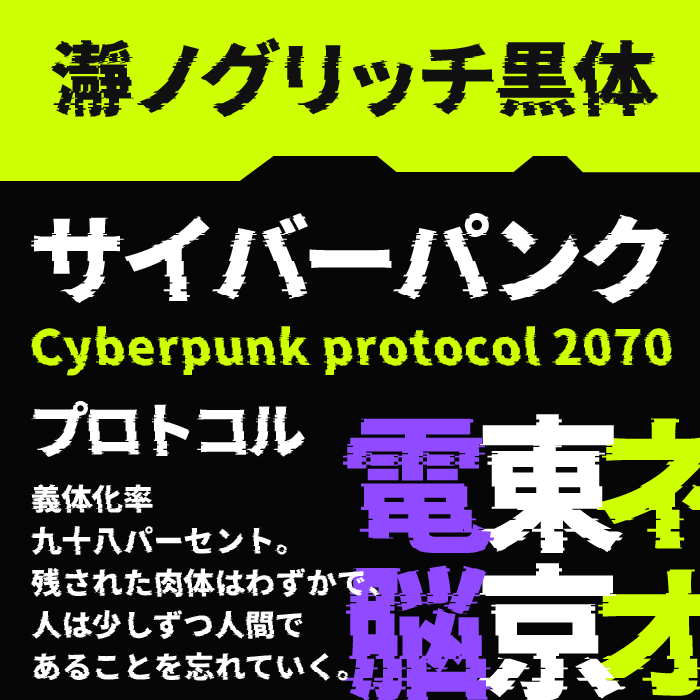
| 活用シーン例 | グリッチ演出、システムエラー表現、退廃的SFデザイン、電脳世界、未来都市ビジュアル |
瀞ノグリッチ黒体は、文字の輪郭がノイズで崩れたようなグリッチ加工が特徴的なフォントです。
通信障害やシステムエラーを連想させるビジュアルが強く、サイバーパンク作品でよく見られる“壊れた未来”や“不安定なデジタル社会”を表現するのにぴったりです。かなりインパクトの強い演出ができます。
ゴチカクット
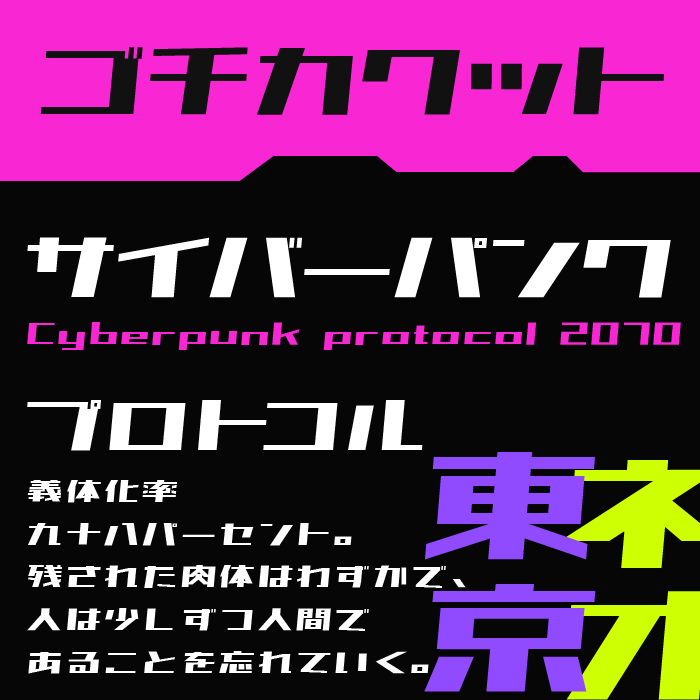
| 活用シーン例 | サイバーパンク作品、近未来UI、SFポスター、ゲームロゴ、電脳都市デザイン |
ゴチカクットは、鋭角的でスピード感のある字形が特徴的なフォントです。
直線を多用したシャープなデザインが近未来的なUIやSF作品を連想させ、無機質でクールな世界観を演出できます。サイバーパンクらしいネオンカラーやハイテク感のあるビジュアルと非常に相性が良く、都市型SFデザインにぴったりなフォントです。
瀞ノクーゲル明朝
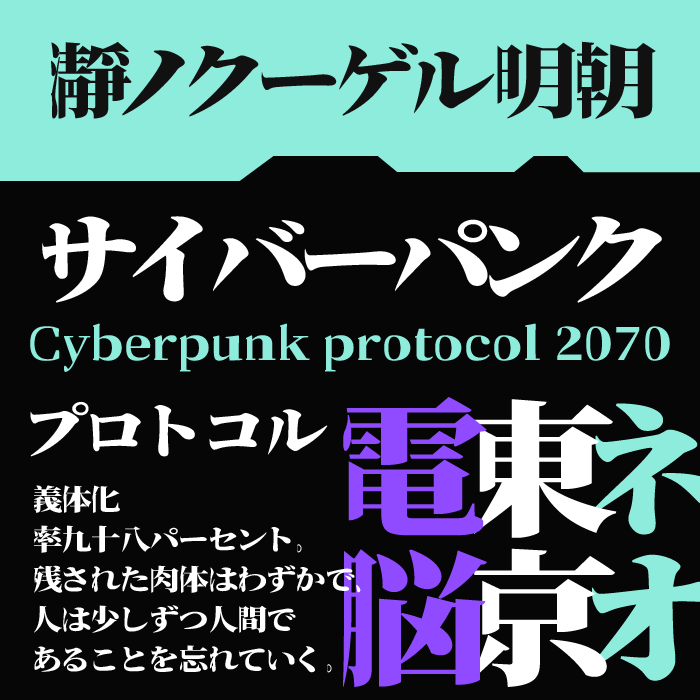
| 活用シーン例 | 広告デザイン/サムネイル/テロップ/バナー/パッケージ/ポスター/同人誌 |
瀞ノクーゲル明朝は、伝統的な明朝体に鋭いエッジや独特な抑揚を加えたフォントです。
クラシカルな雰囲気を持ちながらも、どこか異質で未来感のある造形が特徴で、和とテクノロジーが融合したサイバーパンク作品とも相性抜群です。近未来と退廃感が共存する独特な空気感を演出できます。
JikiTourai
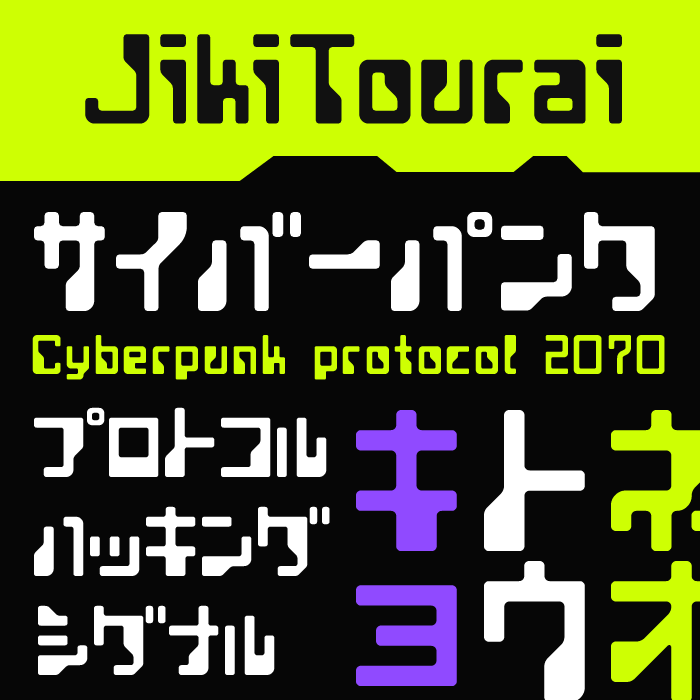
| 活用シーン例 | レトロフューチャー、ゲームUI、ドットデザイン、電子機器風グラフィック |
JikiTouraiは、大胆で太めのドット構造が特徴的なフォントです。
レトロゲームや古い電子機器を思わせるピクセル感がありながら、どこか未来的なインターフェースにも見える絶妙なデザインが魅力です。80年代〜90年代SF作品のようなレトロフューチャー感を表現したい場面におすすめです。
エイプリルゴシック
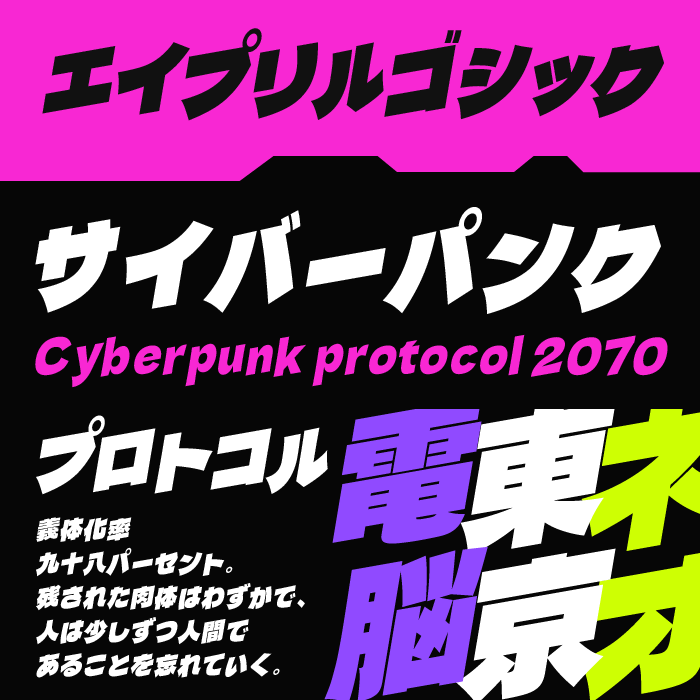
| 活用シーン例 | SFアニメタイトル、近未来レースゲーム、アクション系デザイン |
エイプリルゴシックは、太く傾斜のついたダイナミックな字形が特徴的なフォントです。
勢いのあるフォルムがスピード感やアクション性を感じさせ、アニメ調のサイバーパンク作品や近未来レースゲームのような派手な世界観とよく合います。視線を一気に引き込む強い存在感が魅力です。
Deep South
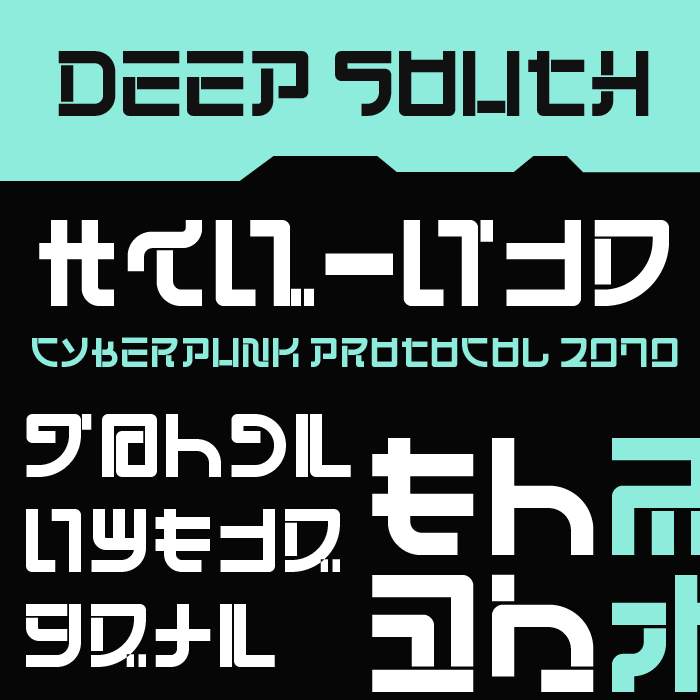
| 活用シーン例 | AIデザイン、未来デバイスUI、テクノロジー系ビジュアル、電子基板風デザイン |
Deep Southは、幾何学的なパーツを組み合わせたような独特な字形が特徴のフリーフォントです。
人工知能や電子基板、未来のデバイス画面を連想させるデザインになっており、かなり無機質でハイテクな印象があります。王道サイバーパンクというより、よりテクノロジー寄りな未来感を表現したい場面におすすめです。
地方野球場電光掲示板
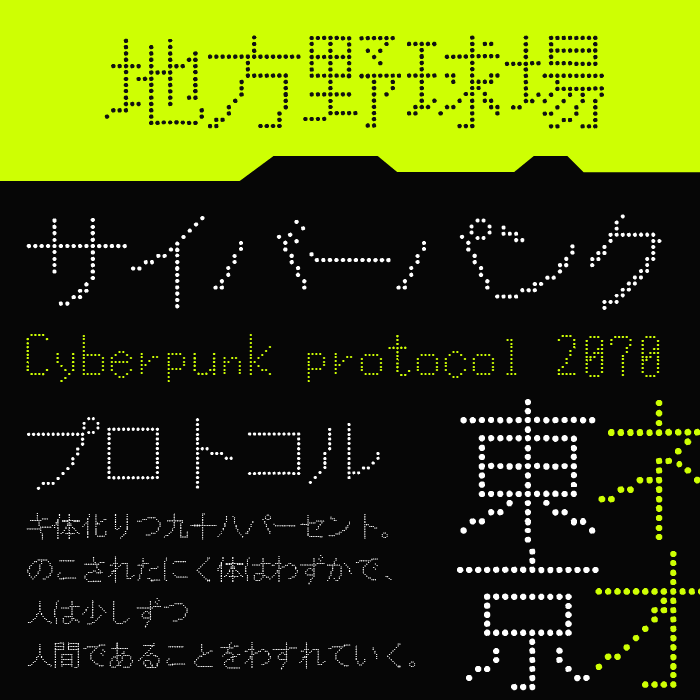
| 活用シーン例 | LED表示風デザイン、ホログラムUI、電光掲示板風演出、未来都市表現 |
地方野球場電光掲示板フォントは、小さなドットを並べて構成された独特な字形が特徴的な、日本語フリーフォントです。一見アナログな電光掲示板を思わせながらも、点で構成された文字表現が未来都市のLED表示やホログラム表示にも見え、独自のサイバーパンク感を演出できます。少し変化球な近未来表現をしたいときにおすすめです。
アルファパーツ
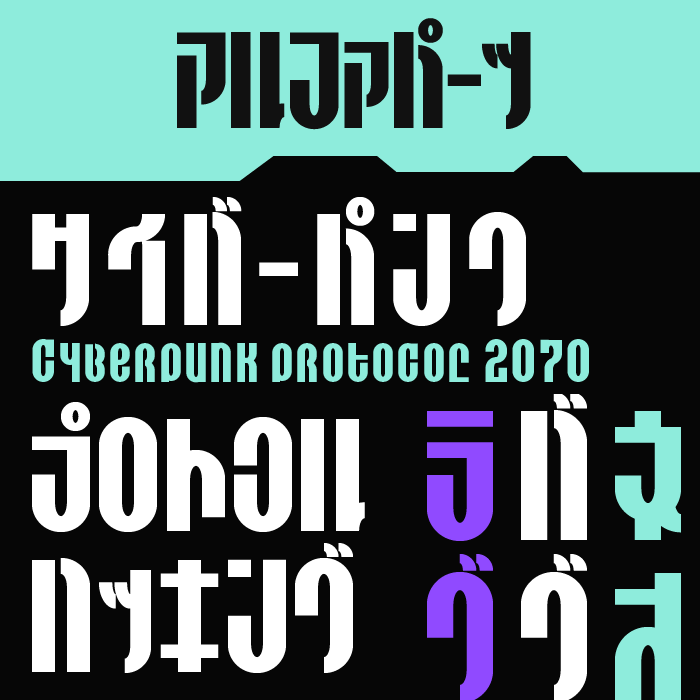
| 活用シーン例 | 海外SF作品風デザイン、映画タイトルロゴ、近未来、サイバー演出 |
アルファパーツは、極端に縦長なシルエットと独特な文字の切れ込みが特徴的なデザインフォントです。海外SF映画のタイトルロゴを思わせる強烈な個性があり、一目で近未来感を演出できます。日本語フォントと組み合わせることで、一気に本格的なサイバーパンク世界観を作り込めます。
でんきチップ
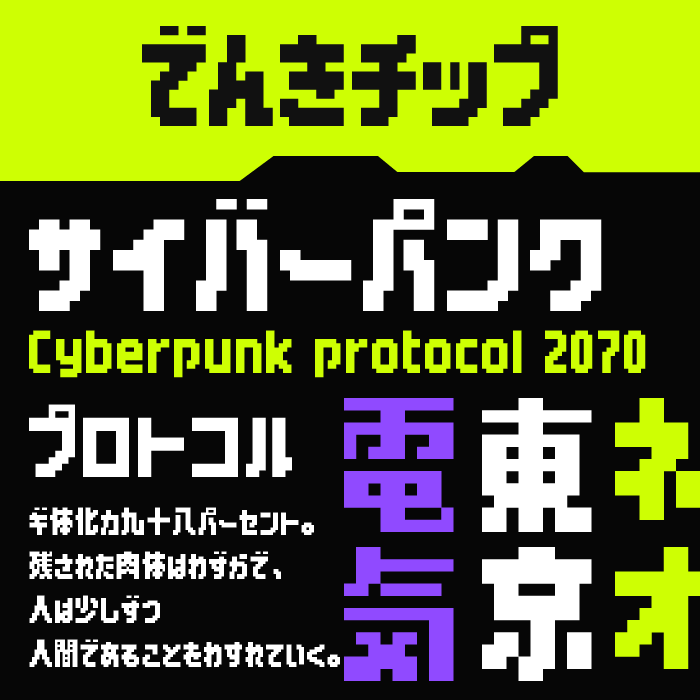
| 活用シーン例 | レトロコンピューター表現、ドットUI、ゲーム風デザイン、機械文明モチーフ |
でんきチップは、クラシックなドットフォントをベースにした、日本語フリーフォントです。ゲーム画面や初期コンピューターを思わせるレトロなデジタル感があり、サイバーパンク作品によくある古い機械文明やアナログとデジタルが混在する世界観にぴったりです。シンプルながら使いやすい万能なドットフォントです。
トロフィシールド
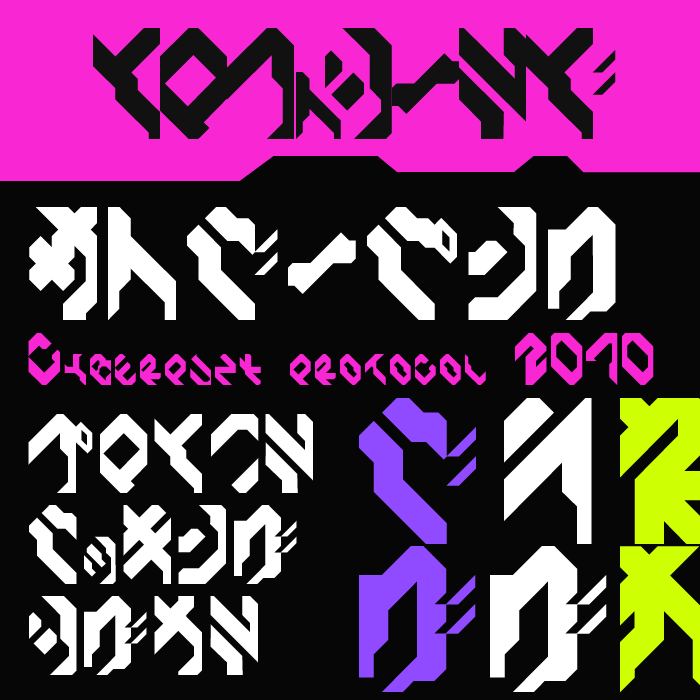
| 活用シーン例 | ハッカー風デザイン、近未来SF作品、電脳世界のUI、ゲームロゴ |
トロフィシールドは、鋭くカットされた多角形のパーツを組み合わせたようなフォントです。
文字そのものが機械部品や電子回路の断片のようにも見え、かなり攻撃的で無機質な近未来感があります。サイバーパンク作品に欠かせないハッキング、AI暴走、企業支配といったダークな未来世界を表現するのにぴったりなフォントです。
MiFファイト
| 活用シーン例 | 近未来UIデザイン、SFポスター、ゲームインターフェース |
MiFファイトは、太めで幾何学的に整理された字形が特徴的な、日本語フリーフォントです。直線と角をベースに構成されたデザインが未来都市のサイン表示やSF映画のインターフェースを連想させ、洗練されたハイテク感を演出できます。クセが強すぎず使いやすいため、王道のサイバーパンク表現にも非常におすすめなフォントです。
マルモニカ
| 活用シーン例 | ドットUI、レトロコンピューター演出、80年代SF作品、電子機器風デザイン |
マルモニカは、粗いドットで構成されたシンプルな字形が特徴的なフォントです。
古い液晶画面や初期コンピューターの表示を思わせるレトロなデジタル感があり、サイバーパンク作品によくある“旧世代の電子機器”や“アナログ感の残る未来”を演出できます。ミニマルながら世界観づくりに強いフォントです。